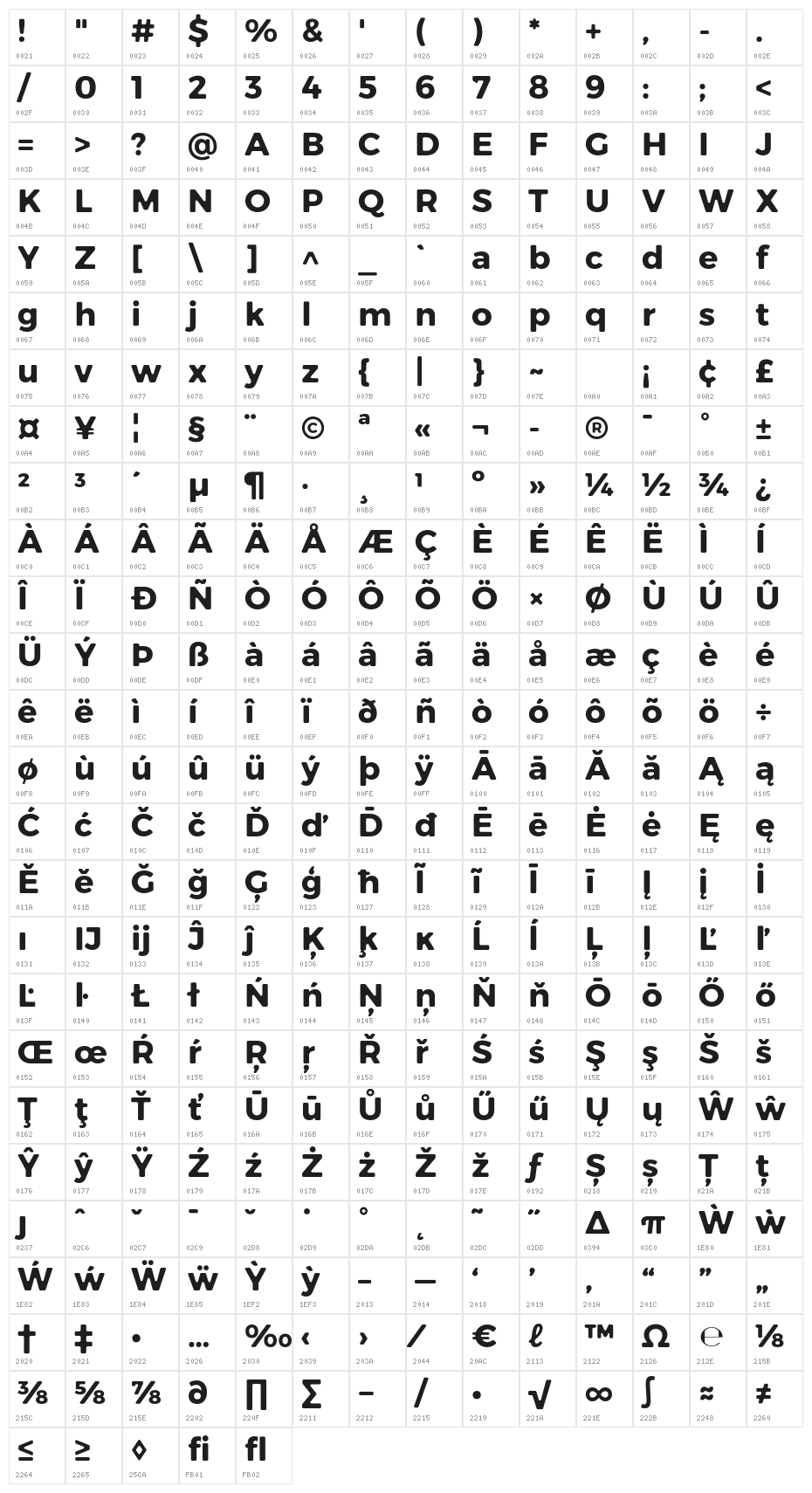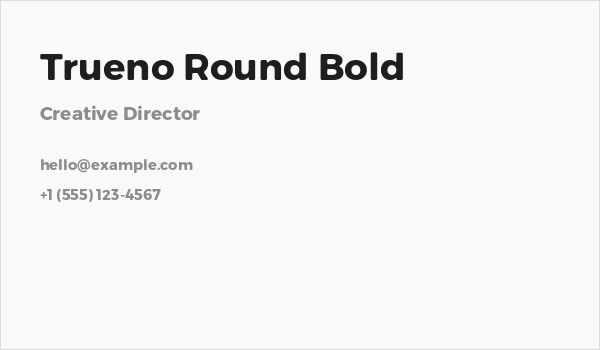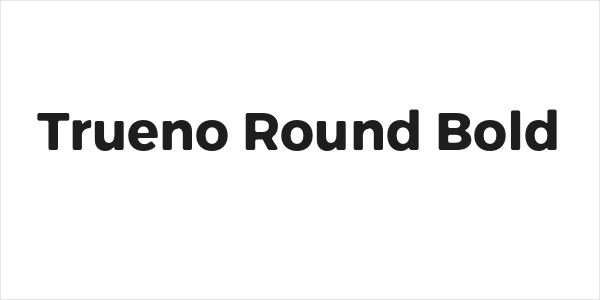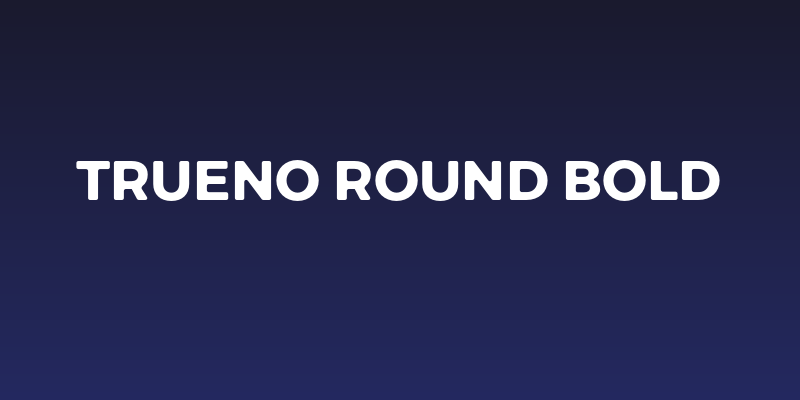
Trueno Round Bold Font
| Anwendungsfall | Headlines, Body text, Logos |
| Vorgeschlagene Projekte | Ideal for branding, advertising, packaging, and digital interfaces where a modern and approachable look is desired. |